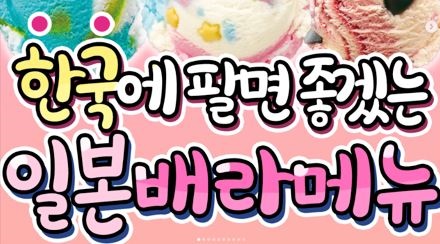
이 폰트 뭔지 알 수 있을까요ㅠㅠ nan*** 2024.07.18 혹시 이 폰트 뭔지 알 수 있을까요ㅜㅜ? 댓글 0 등록 sta*** 빙그레 싸만코체 Bold에 테두리랑 입체 효과를 준 듯하네요 https://www.sandollcloud.com/free-font/16819/Binggrae-Samanco 2024-07-18 답글 달기 댓글 더보기 쉽고 빠르게 가장 비슷한 폰트를 알고 싶다면? 이미지로 검색하기
빙그레 싸만코체 Bold에 테두리랑 입체 효과를 준 듯하네요 https://www.sandollcloud.com/free-font/16819/Binggrae-Samanco